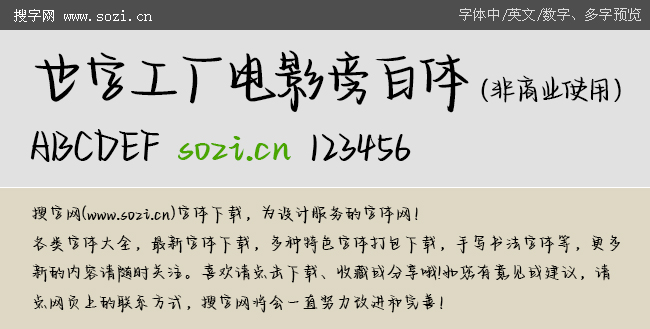
也字工廠電影旁白體
搜字網(wǎng)給大家提供一款也字工廠電影旁白體(非商業(yè)使用)中文字體下載,也字工廠電影旁白體是一款手寫(xiě)書(shū)法字體,字體書(shū)寫(xiě)流暢自然,字形瀟灑大方。具有很好的視覺(jué)效果。適合應(yīng)用于藝術(shù)設(shè)計(jì)、平面宣傳設(shè)計(jì)、網(wǎng)頁(yè)設(shè)計(jì)、海報(bào)設(shè)計(jì)等應(yīng)用(此字體為個(gè)人非商用版,商用可以聯(lián)系:官方網(wǎng)址:https://yefont.com/home,聯(lián)系方式:13798980448)。